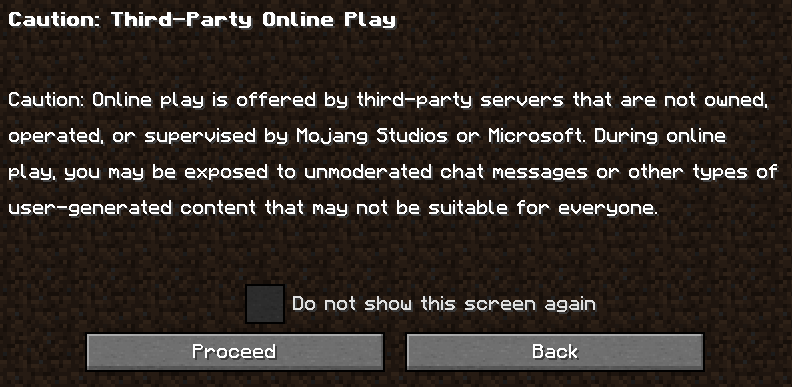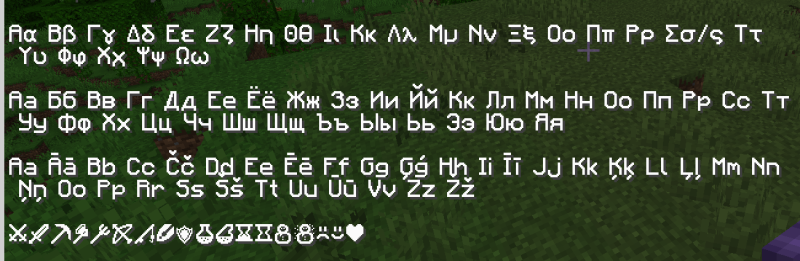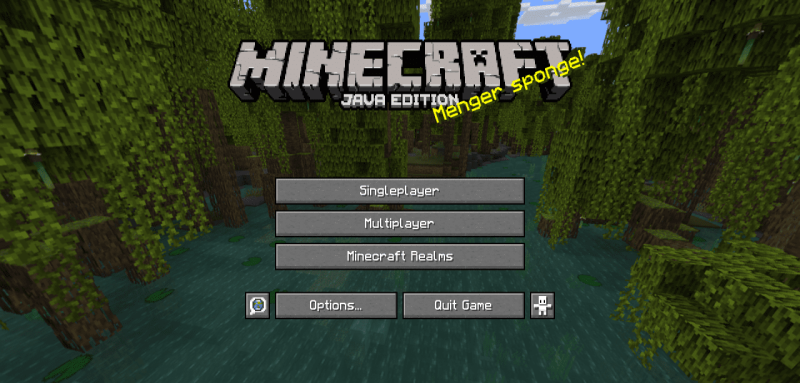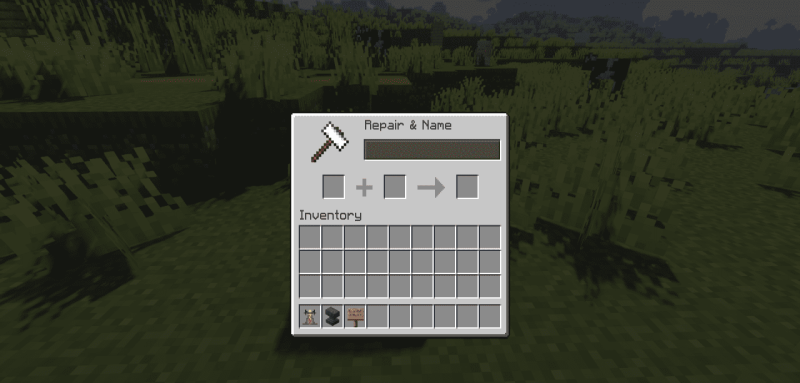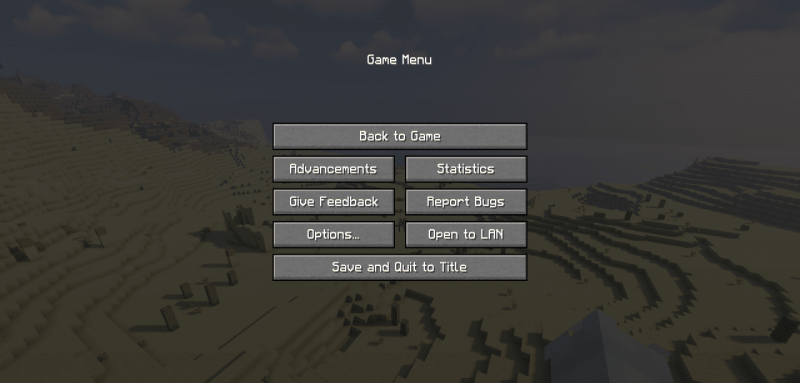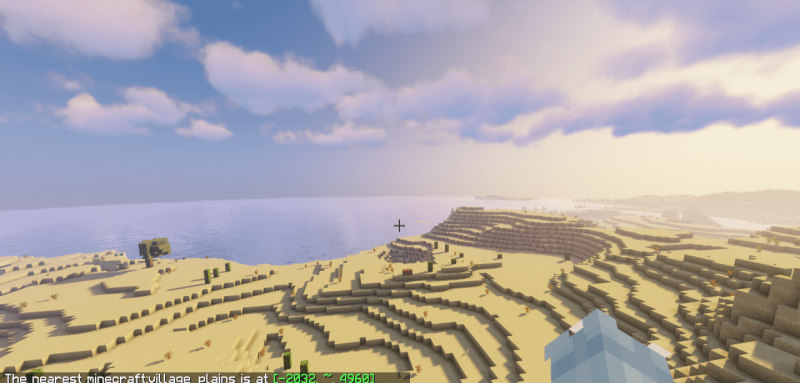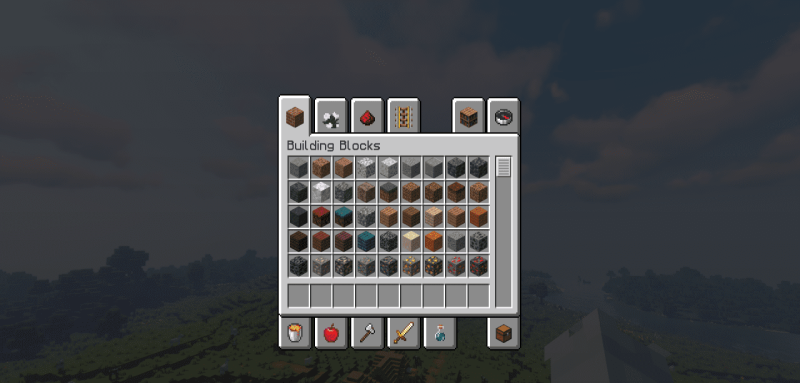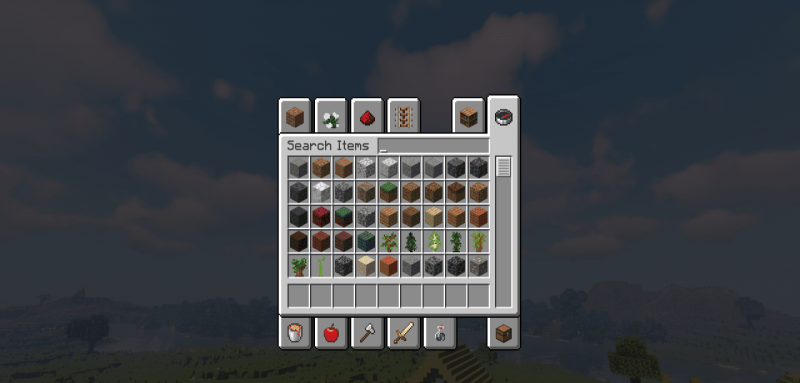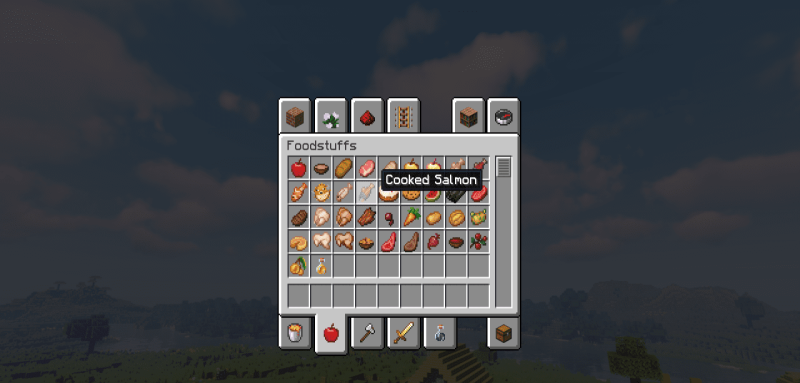
Этот текстурпак представляет собой перерисованную версию стандартного шрифта Minecraft с разрешением 32x, что делает текст более чётким и детализированным, сохраняя при этом оригинальную атмосферу игры. Он идеально подходит для тех, кто хочет улучшить читаемость текста без радикальных изменений визуального стиля.
Особенности текстурпака включают поддержку Unicode-символов, что расширяет возможности отображения текста в игре. Он лицензирован под MIT, что позволяет свободно использовать его в модпаках, видео и стримах.